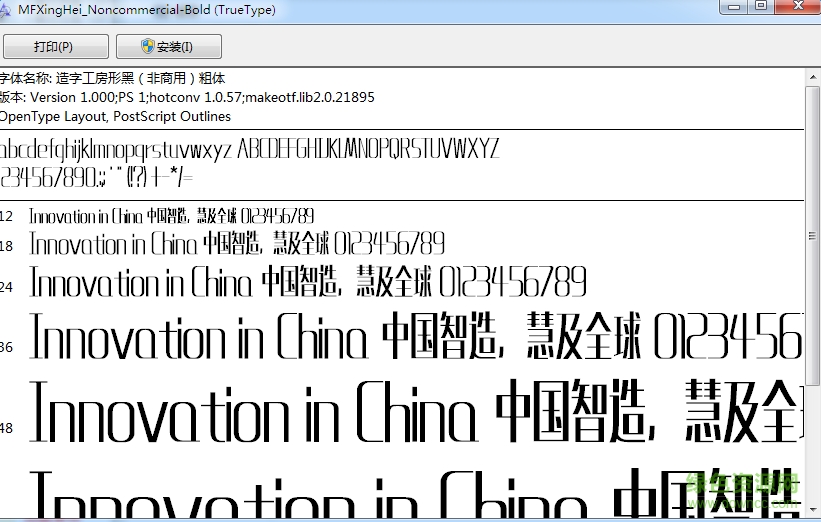
造字工房形黑粗體是一款獨(dú)具特色的電腦字體,筆畫設(shè)計(jì)自然美觀,字形簡(jiǎn)約,曲線優(yōu)美,適用于高端時(shí)尚品牌產(chǎn)品的形象設(shè)計(jì)與推廣。感興趣的朋友可以來綠色資源網(wǎng)下載!
造字工房形黑粗體,字形筆畫簡(jiǎn)約、平直,柔美的弧線讓整體字形更顯干練!精細(xì)的筆畫間凸顯匠師精雕細(xì)琢之力,柔中兼剛不失韌勁。是一款獨(dú)具特色的字體產(chǎn)品!極其適用于科技產(chǎn)品的品牌形象擴(kuò)展。